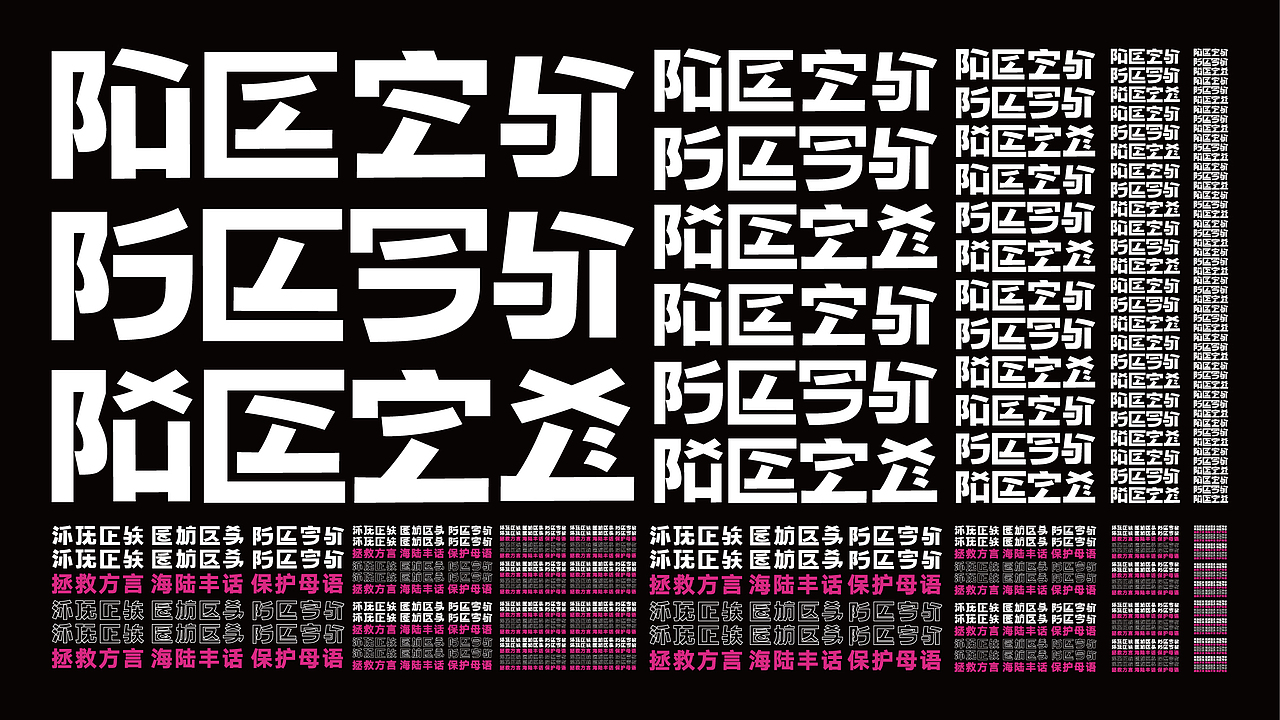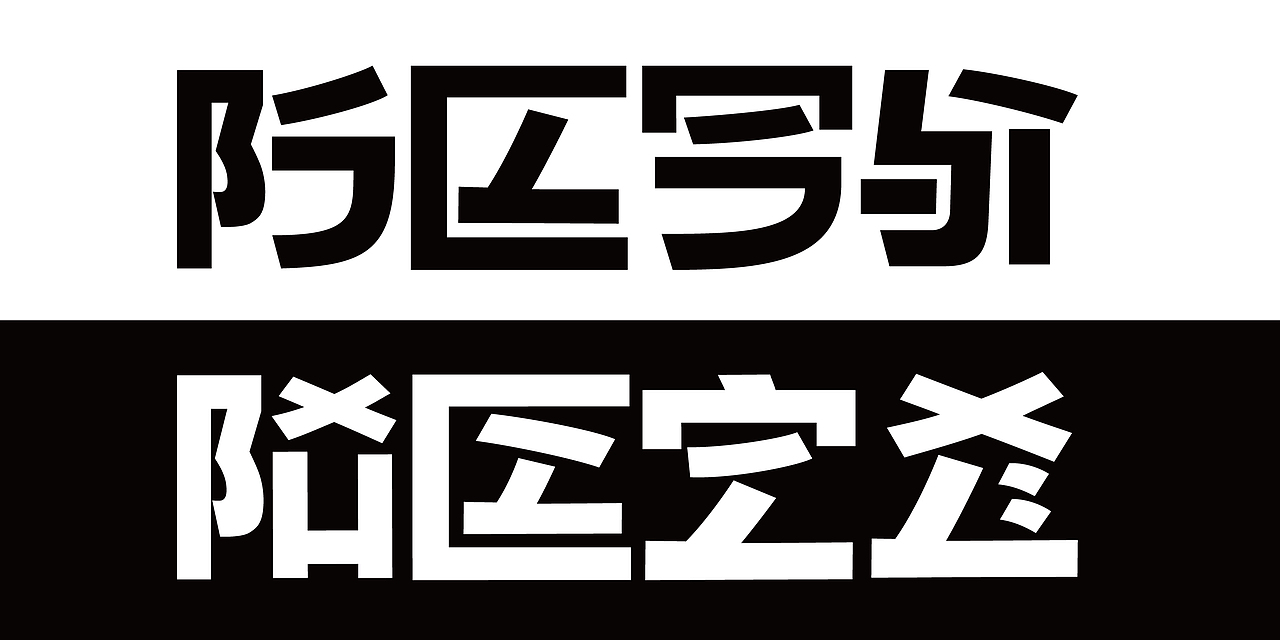
语音文字“龙文”
“语音文字—龙文”的诞生是对家乡方言古语活化的产物,它是一款能够记录海陆丰地区河洛方言语音的文字,由洪茂业先生于上世纪50年代研究至90年代末设计形成的文字体系。这套语音文字系统由64个字符组成(当中不包含兼容符号及情感标记),其中16个声母;48个韵母;外加8调,可形成7000多个不同的音节文字。我对这款文字再设计时,选用了黑体风格,挑战最具难度的正文粗黑体进行设计,做一款可以适合于屏幕显示的龙文字体。从文字设计的未来趋势讲,媒体影像的屏幕阅读是未来字体发展的新领域。黑体文字字形透出的气质更适用于多环境下的编辑字体,粗黑体的字体设计更能使文字具有阳刚之气,有利于在大众在未认识它时的进行有力发声,强化龙文字本身的力量感。
Long Wen, a Phonetic Character, which is a text that can record the voice of Heluo dialect in Hailufeng area. It was studied by Mr. Hong Mao ye in the 1950s and designed by Mr.Hong Mao Ye in the late 1990s.The voice text system consists of 64 characters including 16 initials, 48 vowels and 8 tones, which can form more than 7000 different syllabic characters. (excluding compatible symbols and emotional markers)When I redesigned this text, I chose boldface style which is the most challenging text Body- extra bold design, also made a Long Wen font that can be suitable for screen display. In terms of the future trend of text design, screen reading of media images is a new field of font development. The sans-serif font design can make the text more masculine. The sans-serif font design is conducive to making a strong voice when the public does not know it, and strengthening the power sense of the Long Wen script itself.